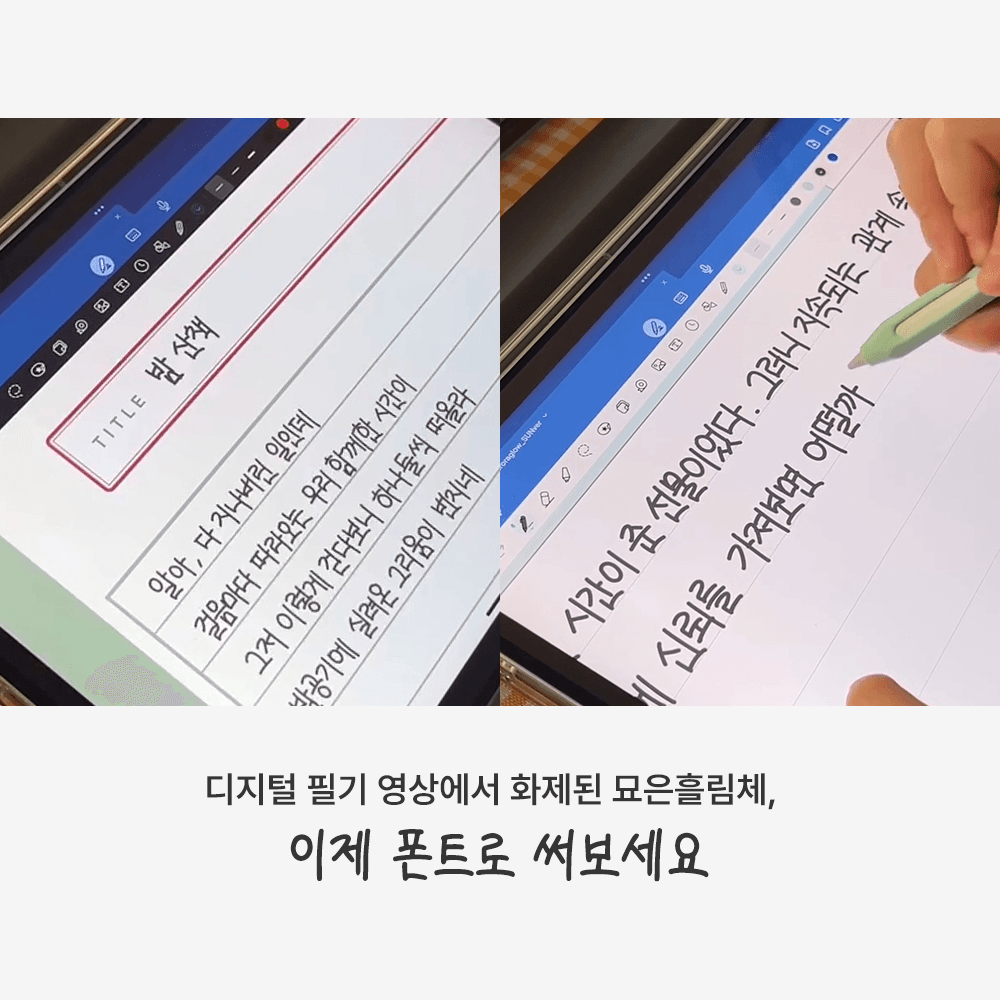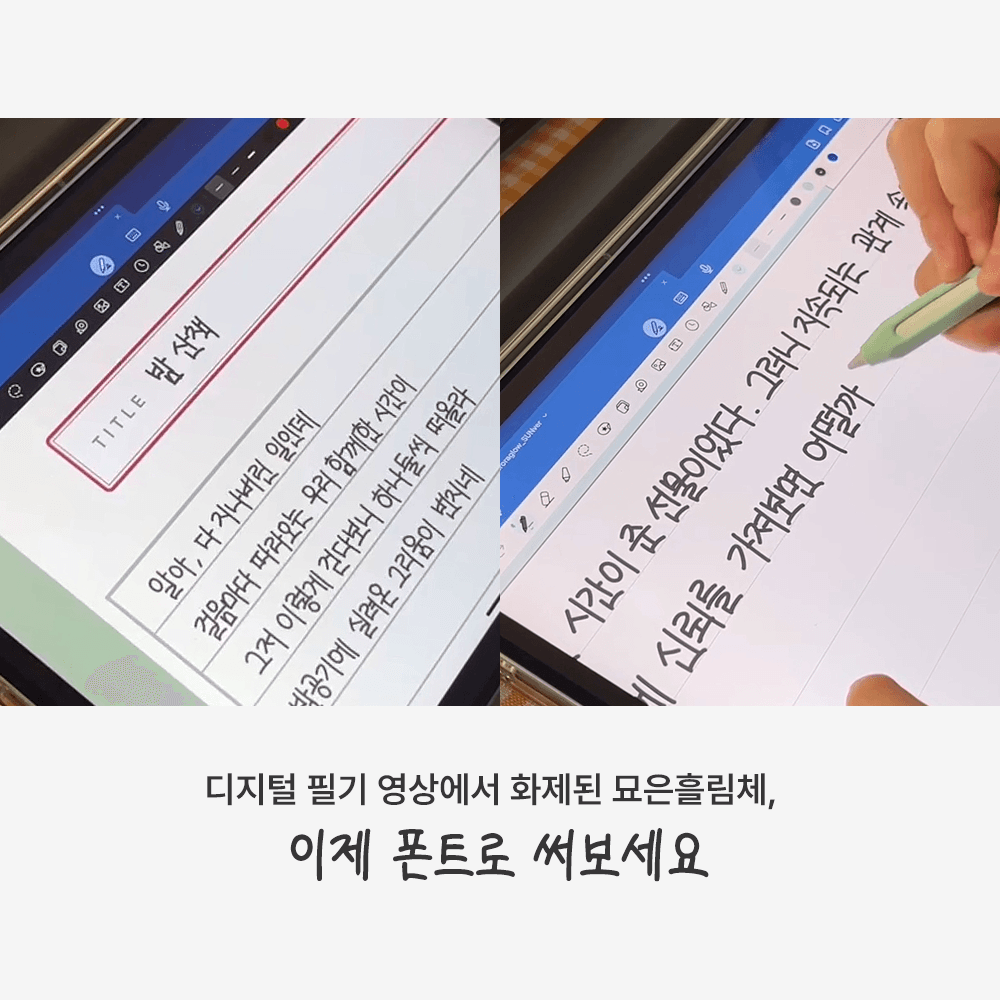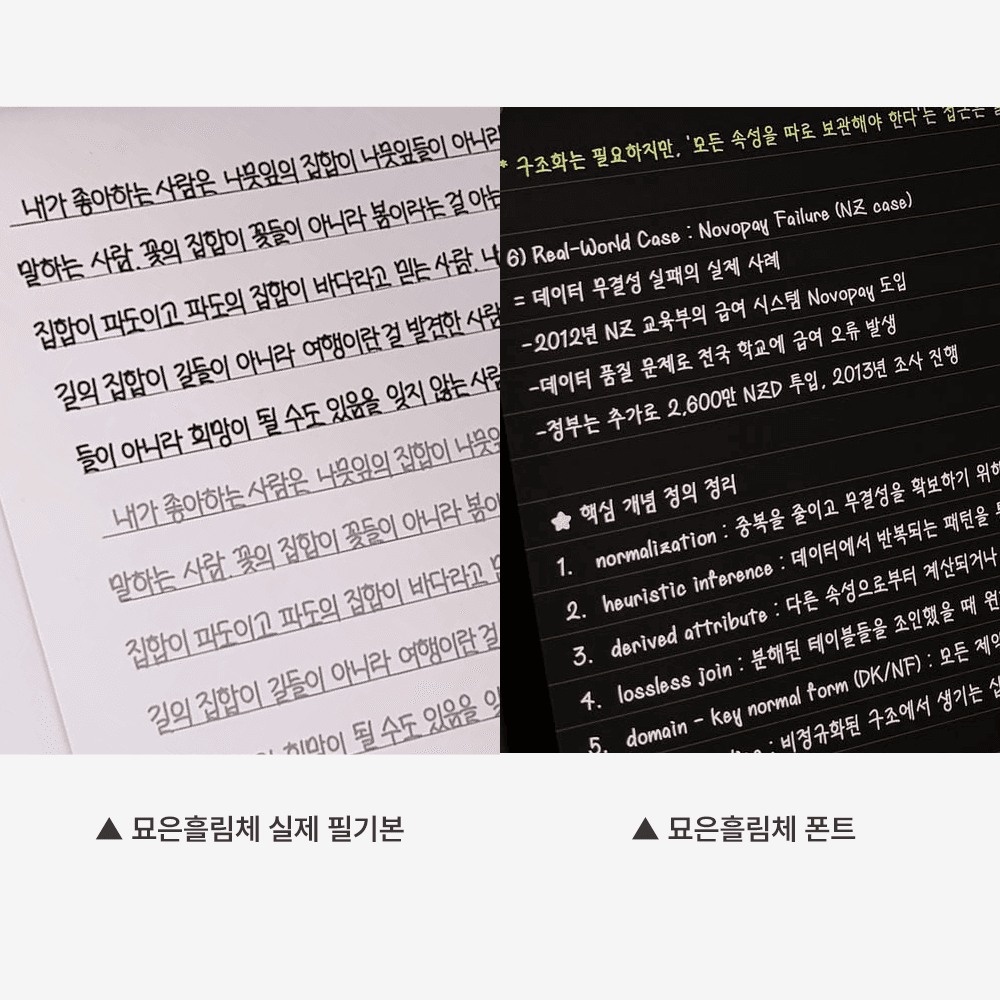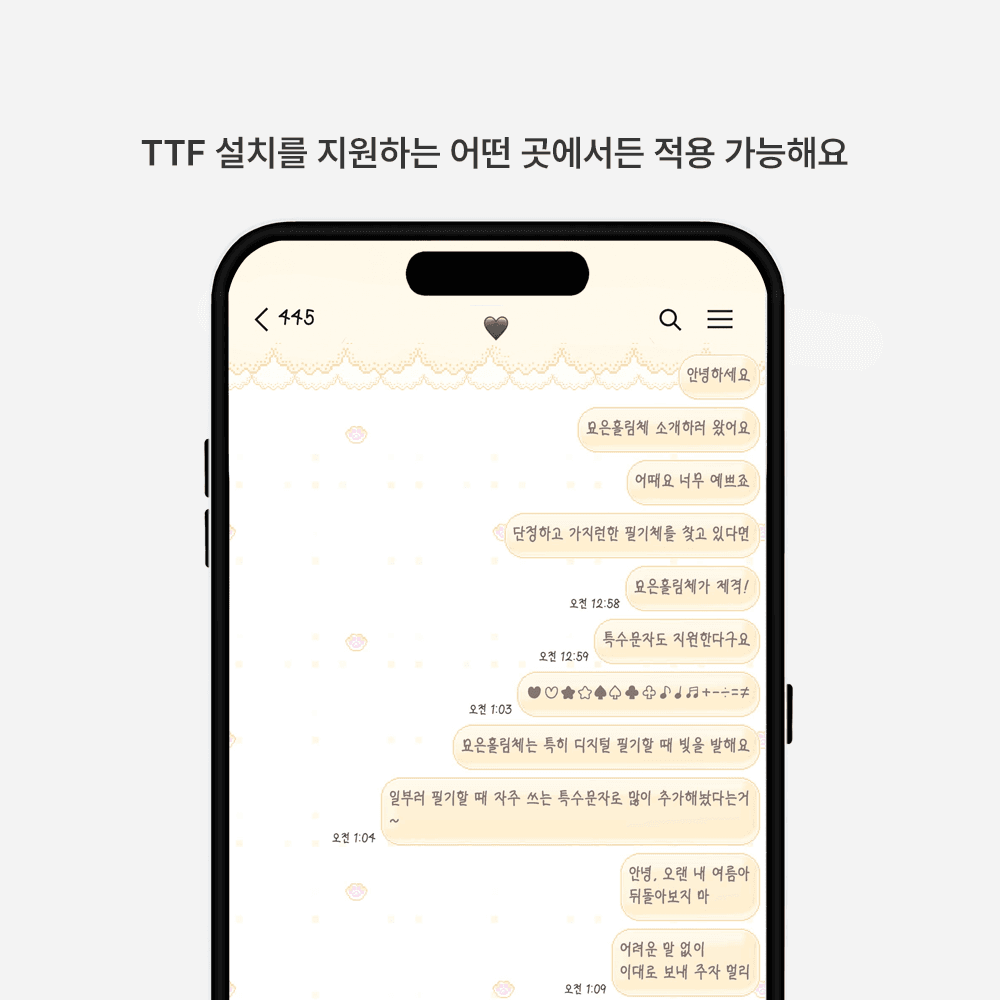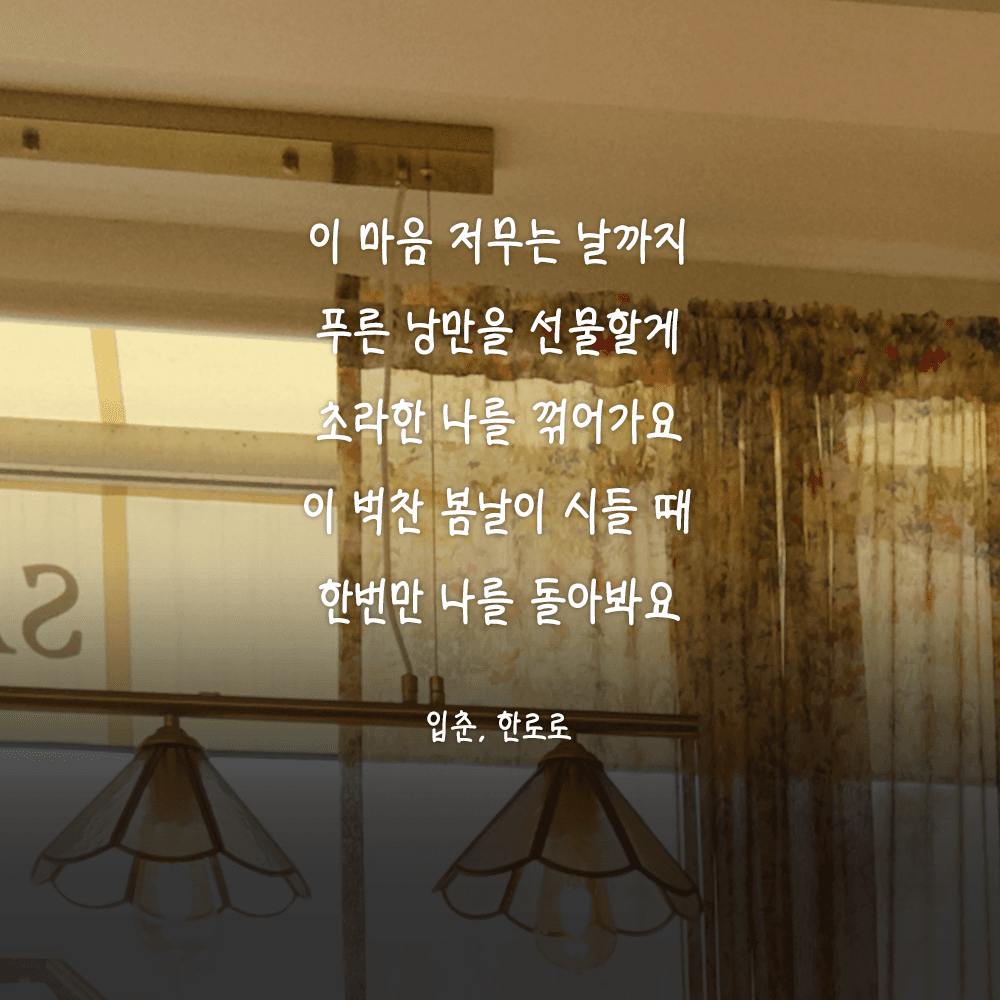
그리운 묘은흘림체
Griun MyoeunHeullim
그리운 묘은흘림체 소개
그리운 묘은흘림체(Griun MyoeunHeullim)는 감성적이면서도 깔끔한 인상을 주는 손글씨 폰트입니다.필기하듯 부드럽게 흘러가는 글씨체라 ‘묘은흘림체’라는 이름을 붙이게 되었어요. 이 폰트는 평소 제가 필기를 할 때 자주 쓰던 손글씨를 바탕으로 만들어졌는데요,그 자연스러운 흐름과 단정한 구조를 더 많은 분들과 나누고 싶어 폰트로 담아보게 되었습니다. 공부할 때, 일기를 쓸 때, 또는 누군가에게 마음을 전할 때, 묘은흘림체가 담백하고 따뜻한 분위기를 더해줄 수 있기를 바랍니다. --- [관리자 공지사항] --- 업데이트 히스토리 ver.1.1 '꿔' 오탈자 이슈로 파일 교체 (2026-06) 페이지 새로고침 후 다운로드 바랍니다. 이용에 불편을 드려 죄송합니다. 🙇